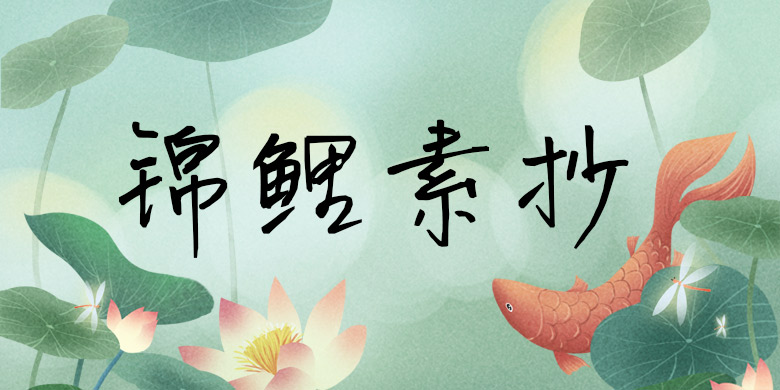
品牌:方正手迹设计师:郭佳发行时间:2018字库编码:大陆简体(GB2312-80)分类:常规书写·硬笔字体属性:精品字
这款字是一种艺术字体,集美之大成。既有很深的传统功力,又具较强的现代气息,笔法细腻,结构严谨,线条遒劲,柔中见刚。字里行间透出从容和优雅,让人赏心悦目,百看不厌。适用于文艺类的书刊、品牌广告和产品包装设计,以及社交网络的个性化用字。